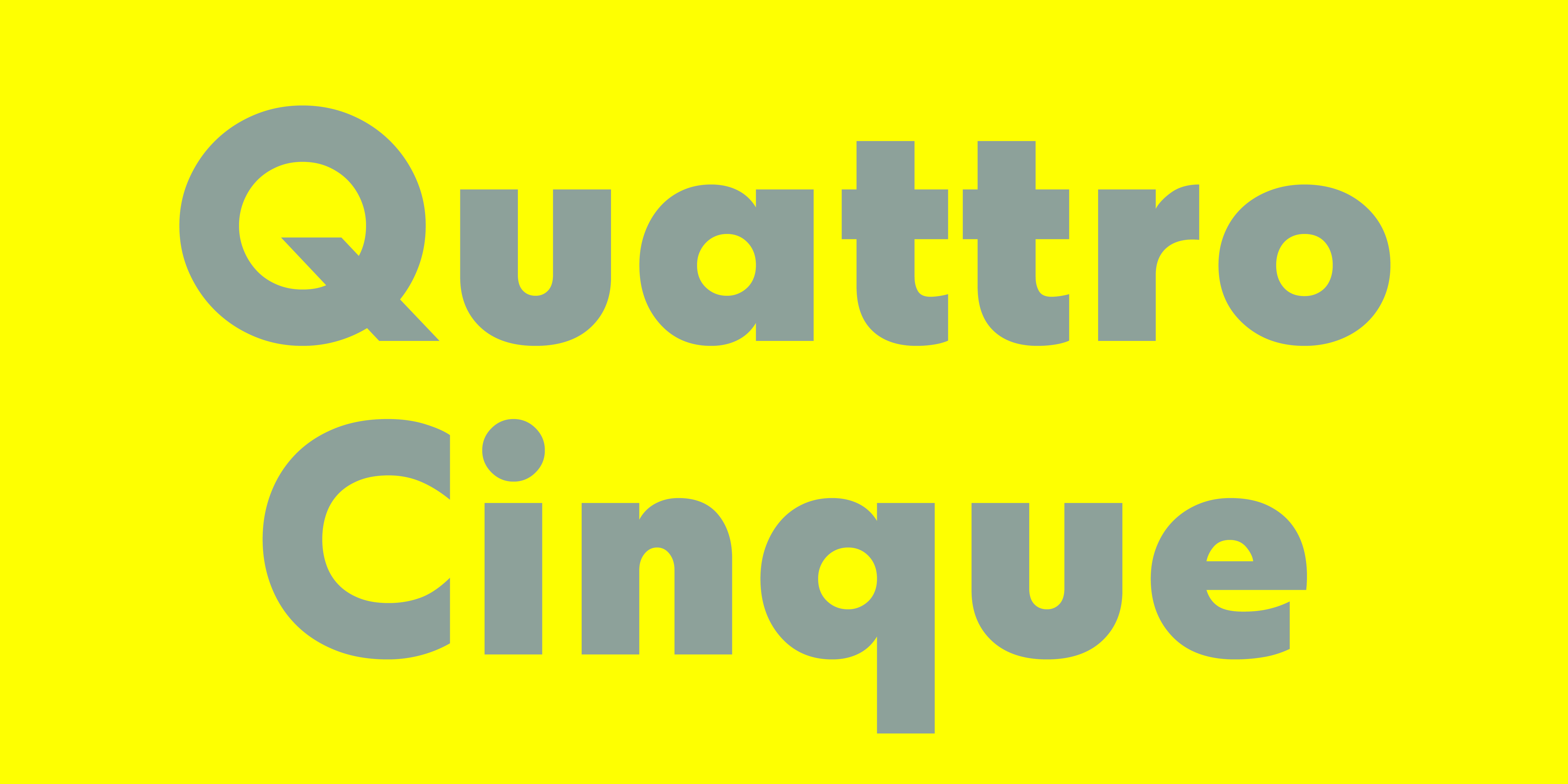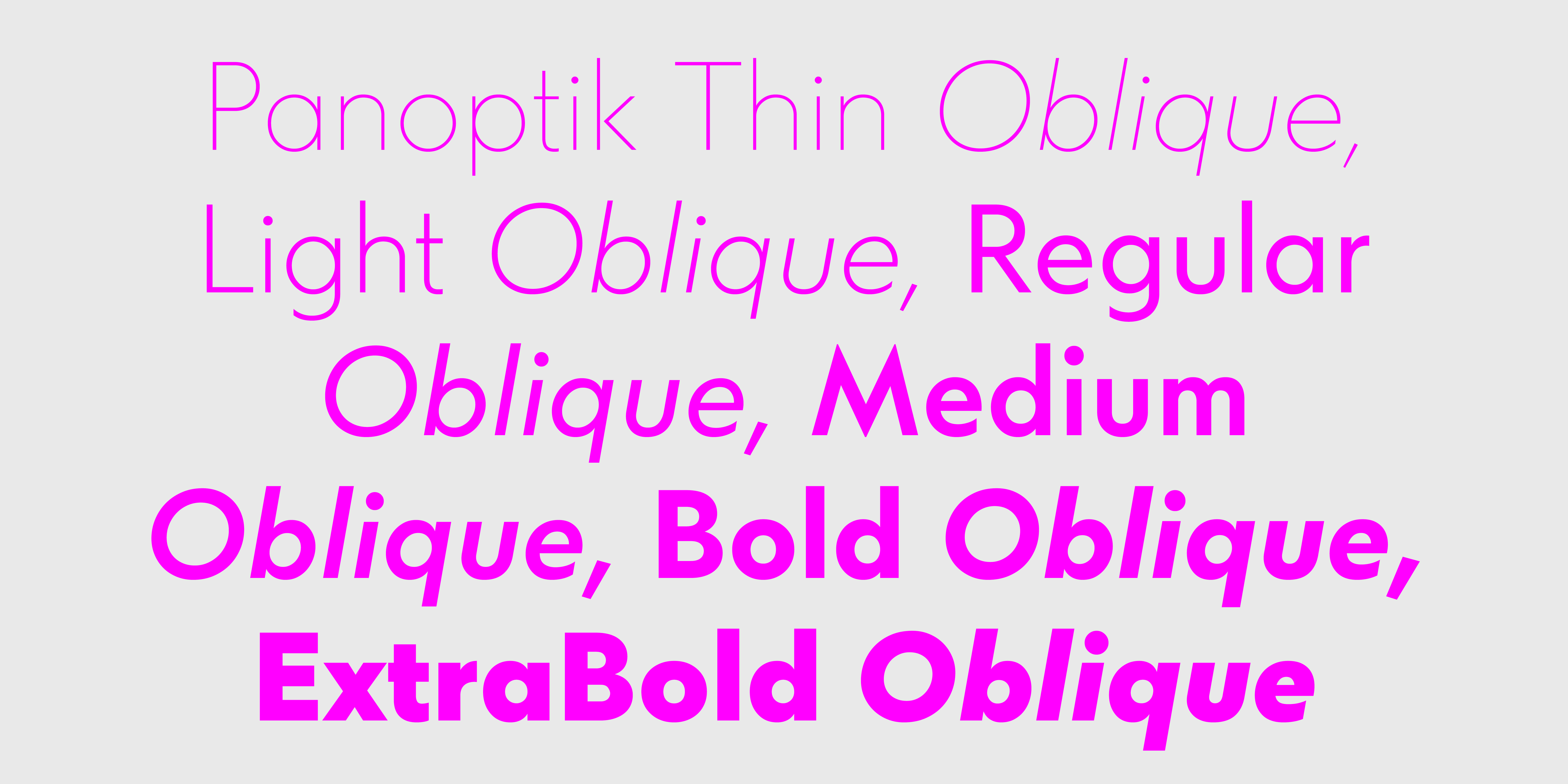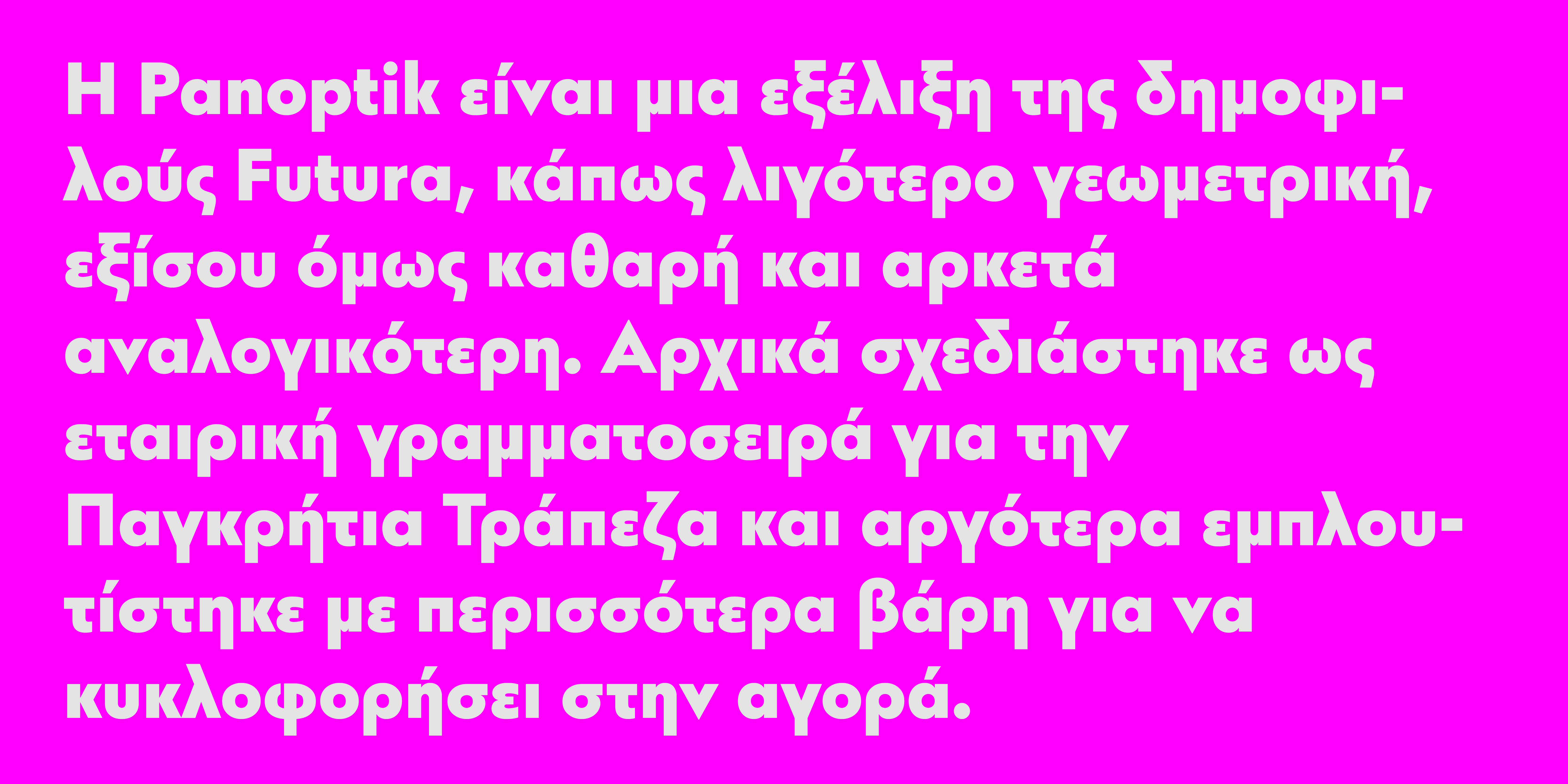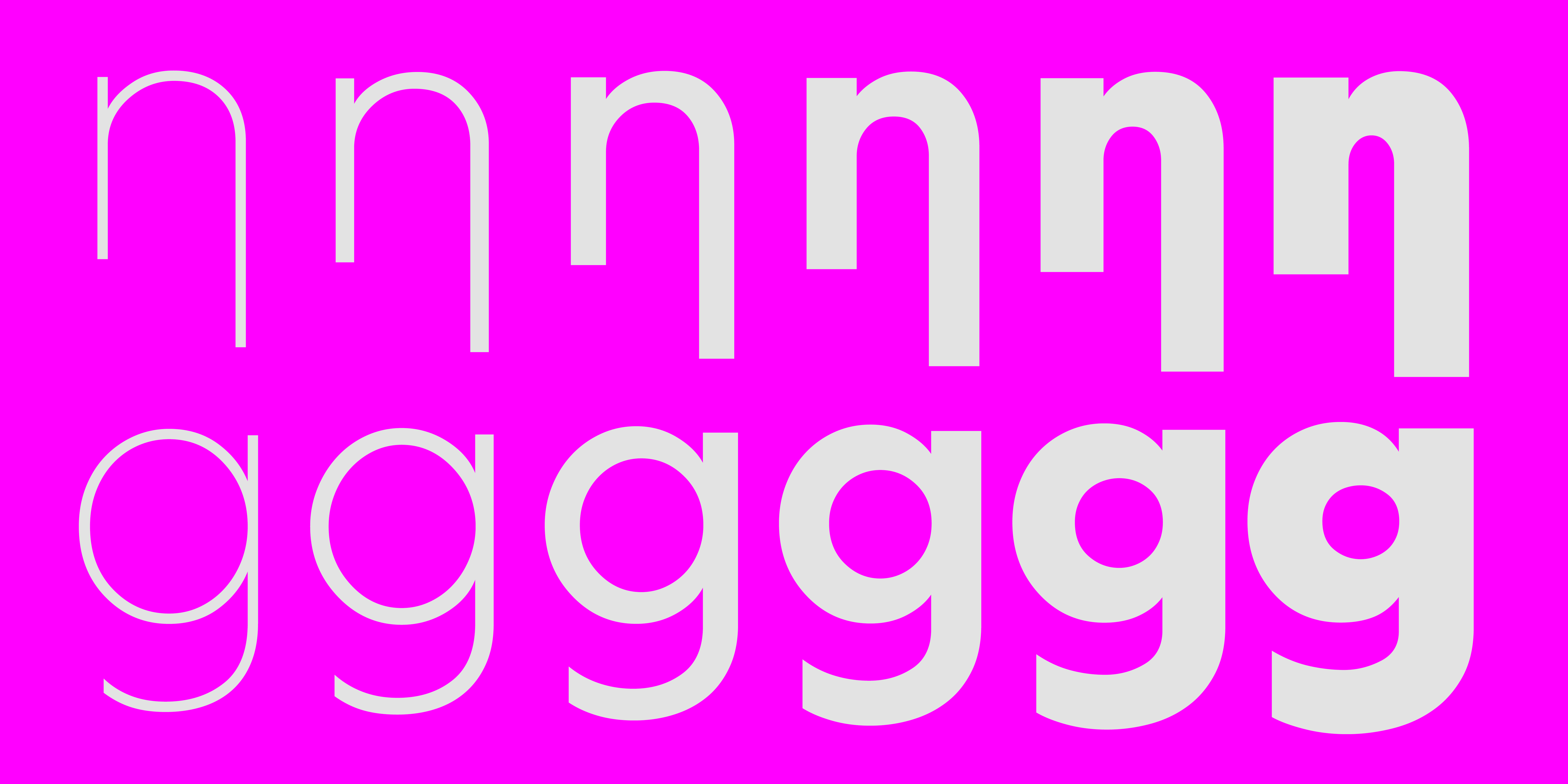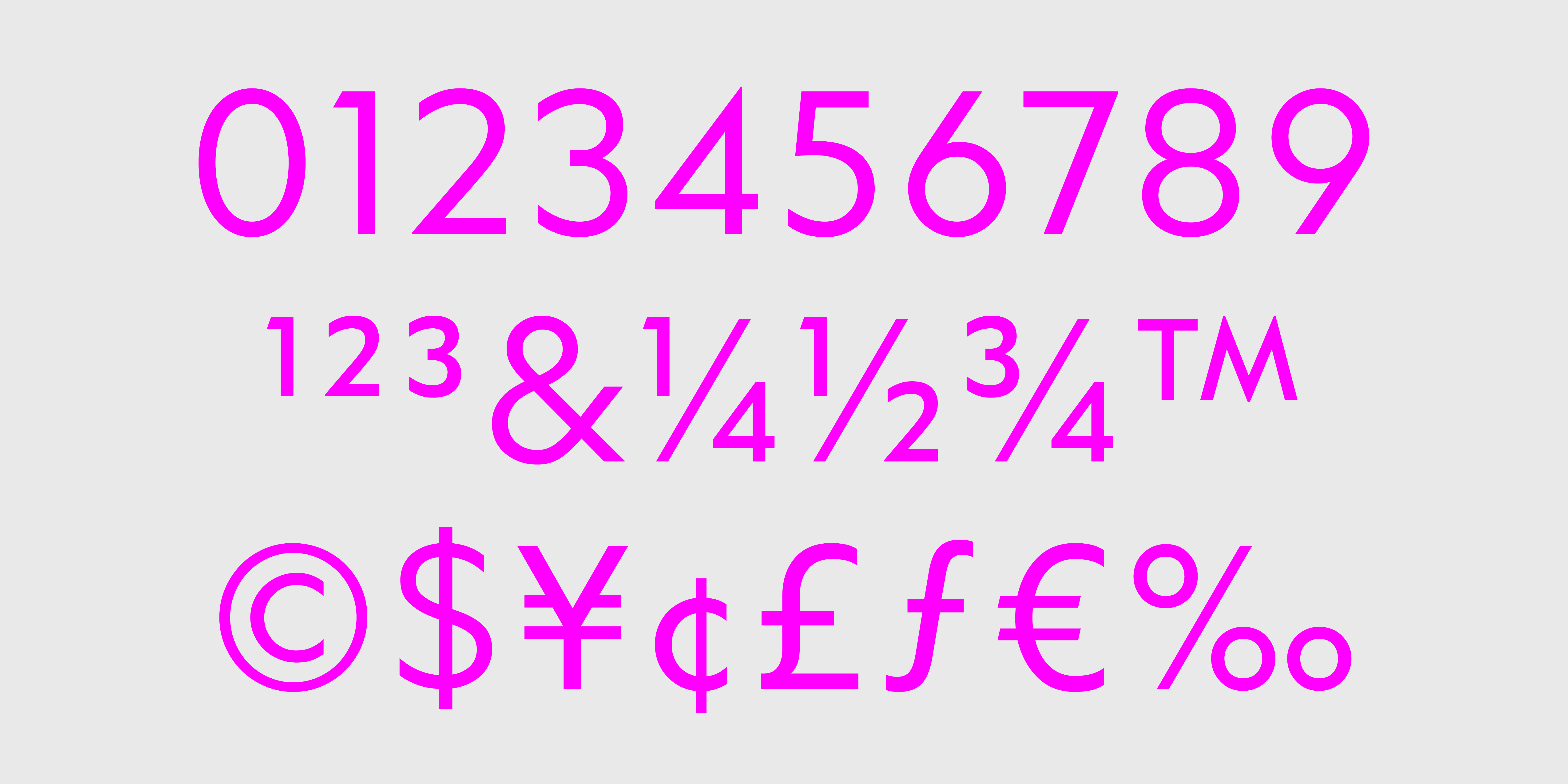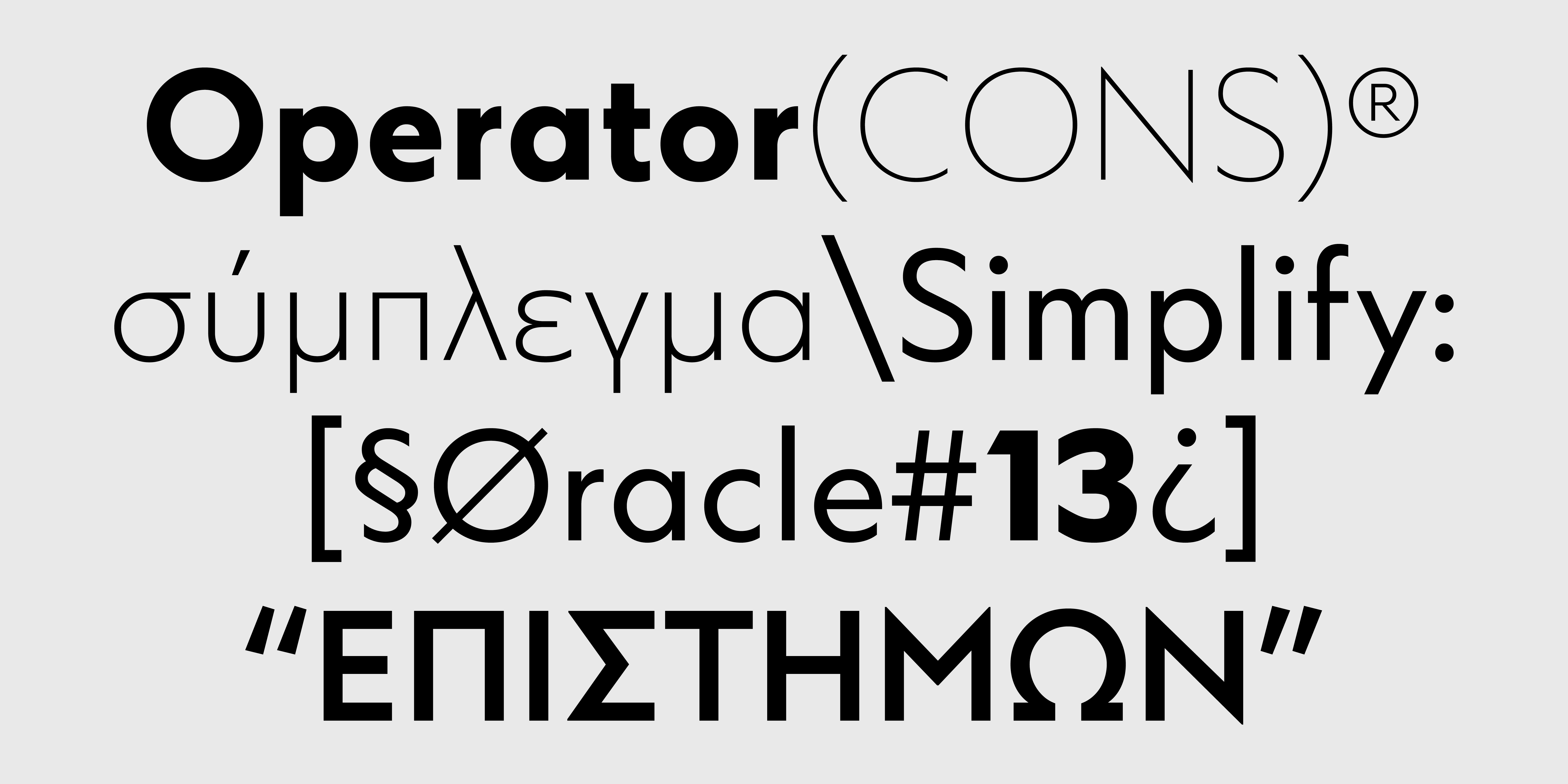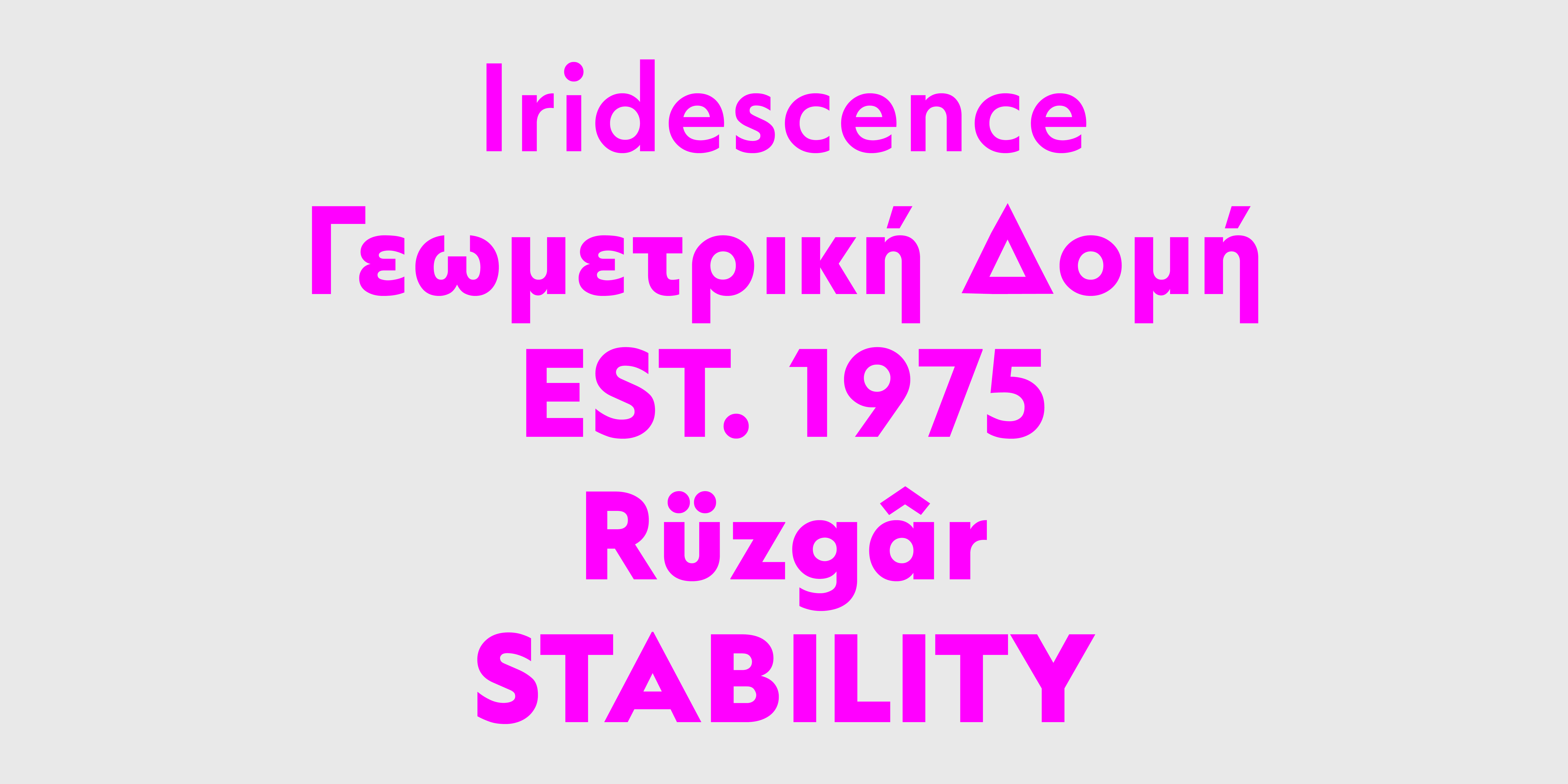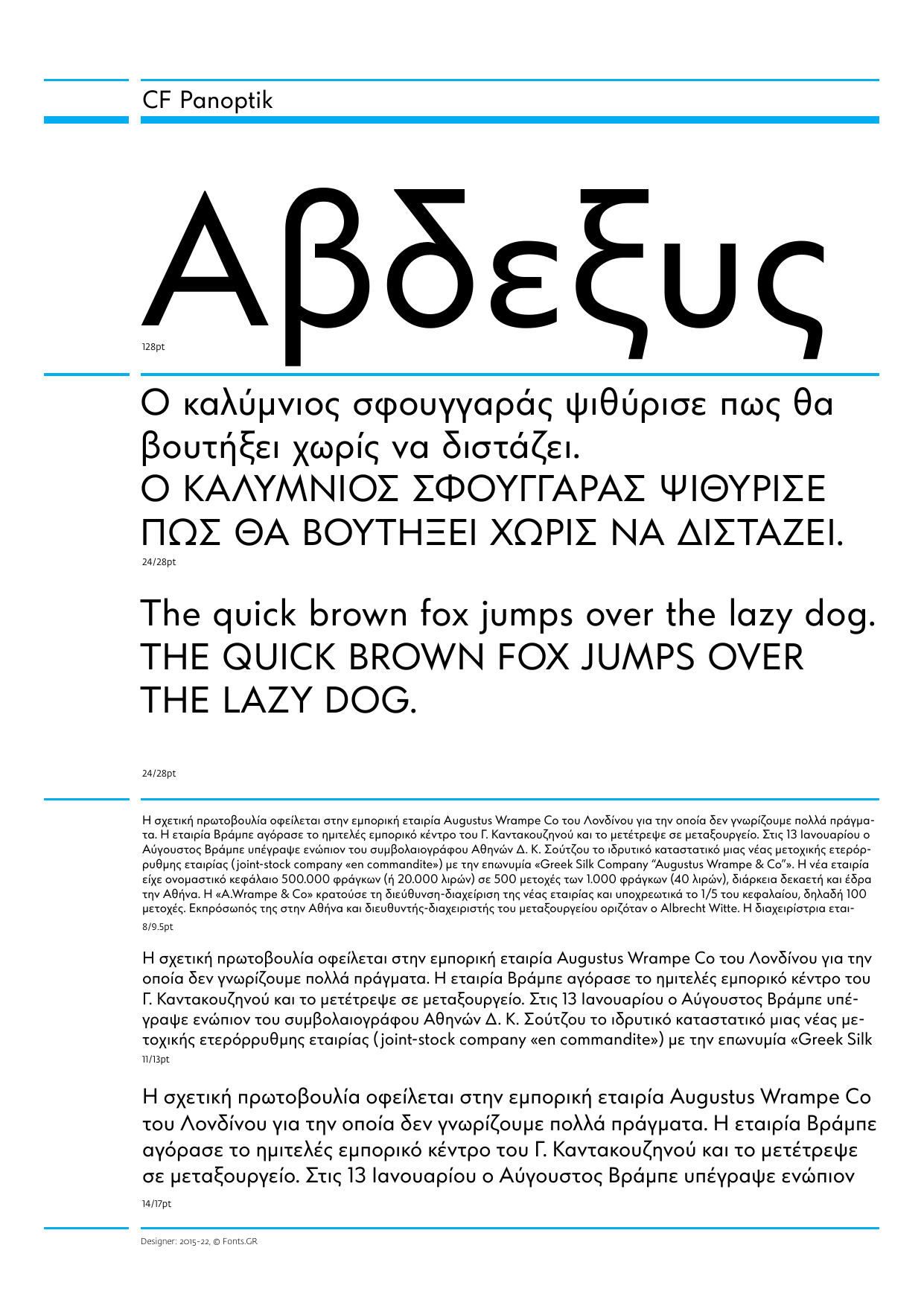
Panoptik
Variable
Η CF Panoptik είναι μια εξέλιξη της δημοφιλούς Futura, κάπως λιγότερο γεωμετρική, εξίσου όμως καθαρή και αρκετά αναλογικότερη. Αρχικά σχεδιάστηκε ως εταιρική γραμματοσειρά για την Παγκρήτια Τράπεζα και αργότερα εμπλουτίστηκε με περισσότερα βάρη για να κυκλοφορήσει στην αγορά. Η τελευταία έκδοση (9/2022) υποστηρίζει και Ελληνικό Πολυτονικό, πλέον του Western, Extended Latin και Μονοτονικού. Είναι διαθέσιμη και σε Variable αρχείο χωρίς επιπλέον χρέωση.
Historical Forms
s
Standard Ligatures
ffi
ffl
ff
fi
fl
ſt